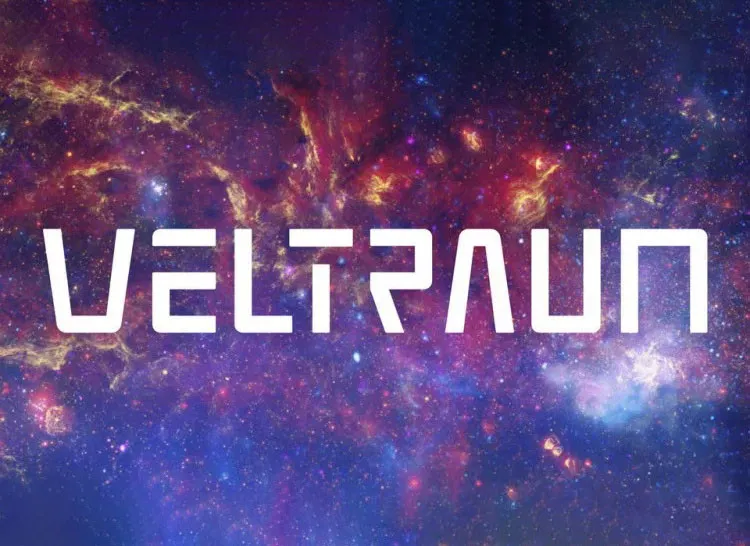
Esta fonte chamada Weltraum é uma união nobre e elegante perfeita para ambientes digitais modernos. Ela foi criada por Johannes Pistorius, um designer de fontes reconhecido. Com seu estilo minimalista e futurista, mas sempre preocupado com a funcionalidade e legibilidade, Weltraum é uma escolha ideal para quem busca uma aparência elegante sem abrir mão da precisão visual necessária em textos digitais. Suas linhas simples e efêmeras criam um ar de modernidade que se encaixa perfeitamente em qualquer projeto de design digital. Ideal para criar headlines atraentes, graficos de alta qualidade ou qualquer texto que deseje destacar, Weltraum é uma ótima adição ao seu portfólio de fontes. Combinada com qualquer tipo de conteúdo digital, ela criará um efeito visual envolvente e natural.